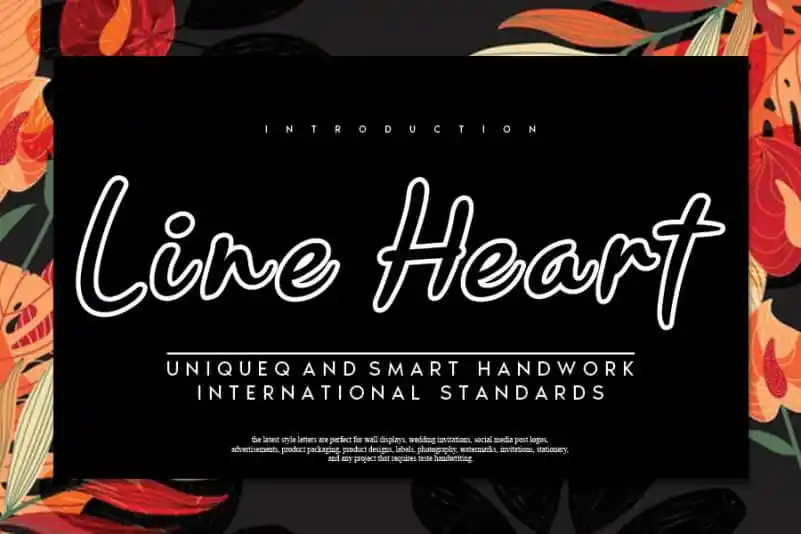
Line Heart Script Font
A ‘Line Heart Script Font’ é uma fonte script curta e fluida que traz um toque incrivelmente alegre às suas criações. Seja para cartões personalizados, posters artísticos ou qualquer outro design, essa fonte é capaz de dar vida aos seus ideais criativos, destacando-os em meio ao caos visual. Suas linhas delicadas e sentimentos expressivos são perfeitos para aqueles que buscam um toque romântico ou elegante nos projetos. Seja qual seja o projeto, a ‘Line Heart Script Font’ é uma escolha versátil e encantadora, tornando suas criações únicas e memoráveis. Descubra como essa fonte única pode transformar seus próximos designs em verdadeiros trabalhos de arte.